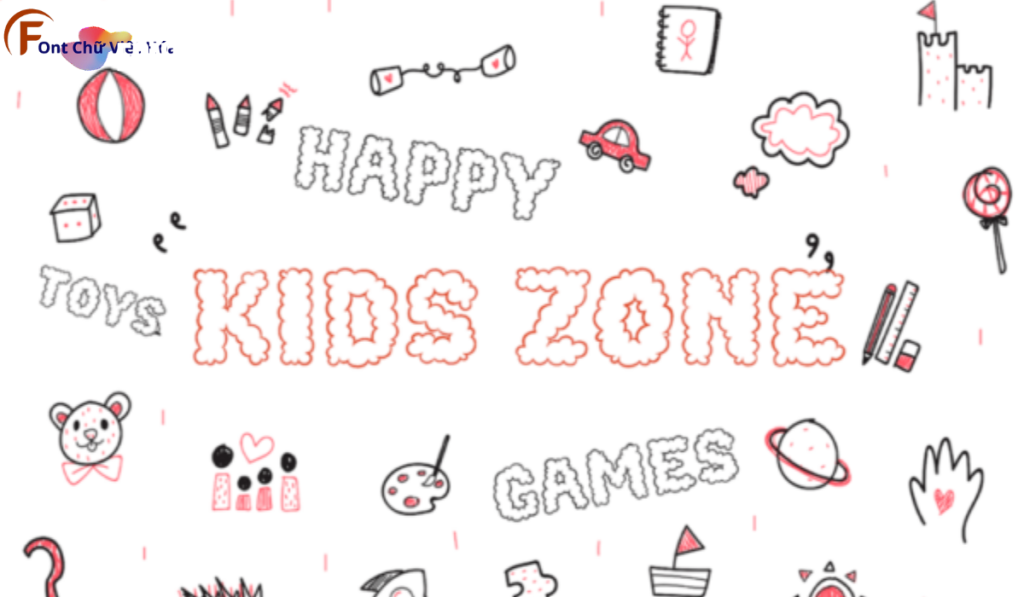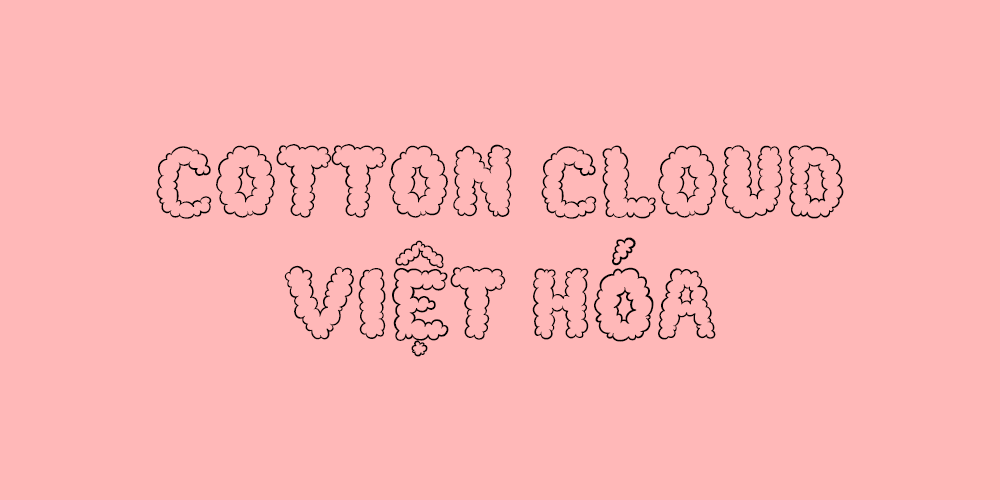
Font 1FTV Cotton Cloud
Font 1FTV Cotton Cloud là một font chữ độc đáo, thuộc bộ 1FTV, nổi bật với phong cách sans-serif hiện đại và các đường nét mềm mại, bồng bềnh. Thiết kế của 1FTV Cotton Cloud tập trung vào sự nhẹ nhàng và dễ đọc, đặc biệt phù hợp cho các thiết kế đòi hỏi tính thẩm mỹ cao như poster, logo, và tiêu đề. Với tỷ lệ chữ cân đối và các đường nét rõ ràng, font này tạo ra ấn tượng thị giác mạnh mẽ và giúp tối ưu hóa không gian trong thiết kế. Font này cũng đã được Việt hóa, mang đến sự linh hoạt và tiện dụng cho các dự án thiết kế bằng tiếng Việt